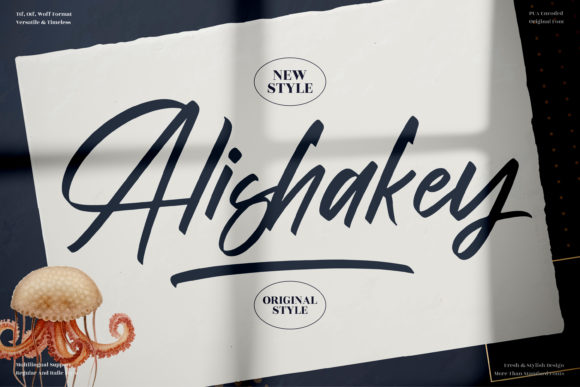
[Creativefabrica] Alishakey Font (2021)
Alishakey - это прекрасный и нежный шрифт, который излучает элегантность и класс.
Этот шрифт был создан специально для тех, кому нужен красивый и освежающий вид их дизайна.